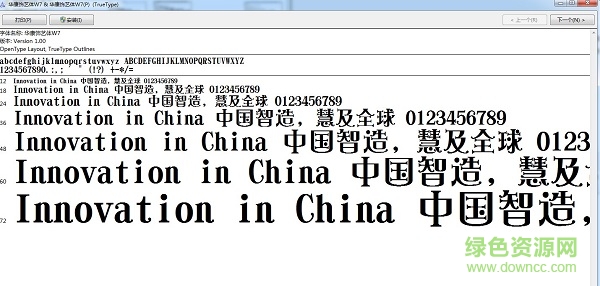
華康飾藝體 std w7字體
華康飾藝體dfshiyiw7是一款字形華美的美術(shù)字體,字形構(gòu)思精巧、線條錯落有致,新穎獨特,視覺效果出眾,可用于廣告、影視、海報等各個領(lǐng)域,喜歡的朋友快來下載吧!
華康飾藝體特點
字體特色為橫細直粗,筆劃的起筆與收筆加入西方文字的襯線裝飾,帶著一股濃濃的華麗復(fù)古感,造型復(fù)古、優(yōu)美,卻又散發(fā)活潑氣息,猶如西文的花體字。適合各類標題、廣告雜志的應(yīng)用。
華康飾藝體w7(p)